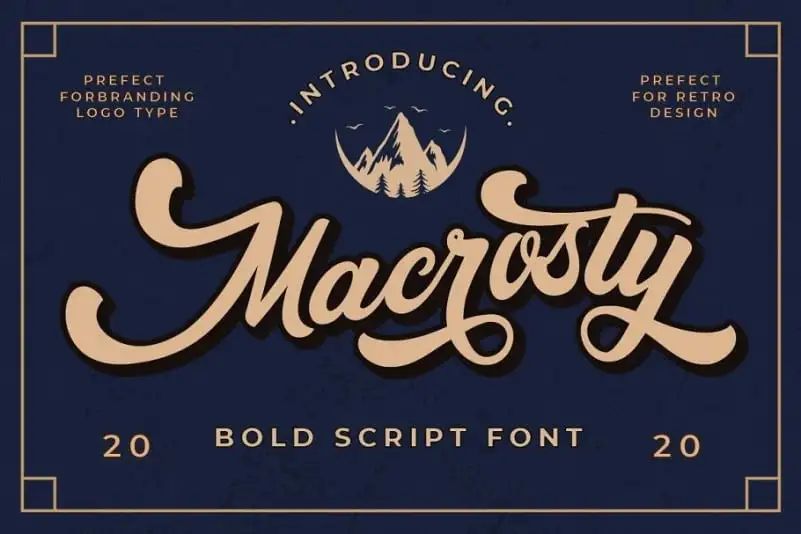
Macrosty Script Font – Download Grátis
Introduzimos Macrosty Script Font, uma tipografia escrita à mão que foi projetada para logos. Esta fonte tem um estilo audacioso e perfeito para quem busca uma tipografia adequada para temas vintage ou retro. Desenvolvida pelo font designer PutraCetol Studio, esta tipografia inclui letras maiúsculas, minúsculas, sinais de pontuação, símbolos e números, alternativas e muito mais. O Macrosty Script Font também é altamente personalizável e suporta múltiplas línguas, incluindo caracteres Unicode Proportional Typography Access (PUA) codificados. É uma ótima escolha para aqueles que desejam dar um toque de estilo e originalidade a seus projetos gráficos retro ou vintage.